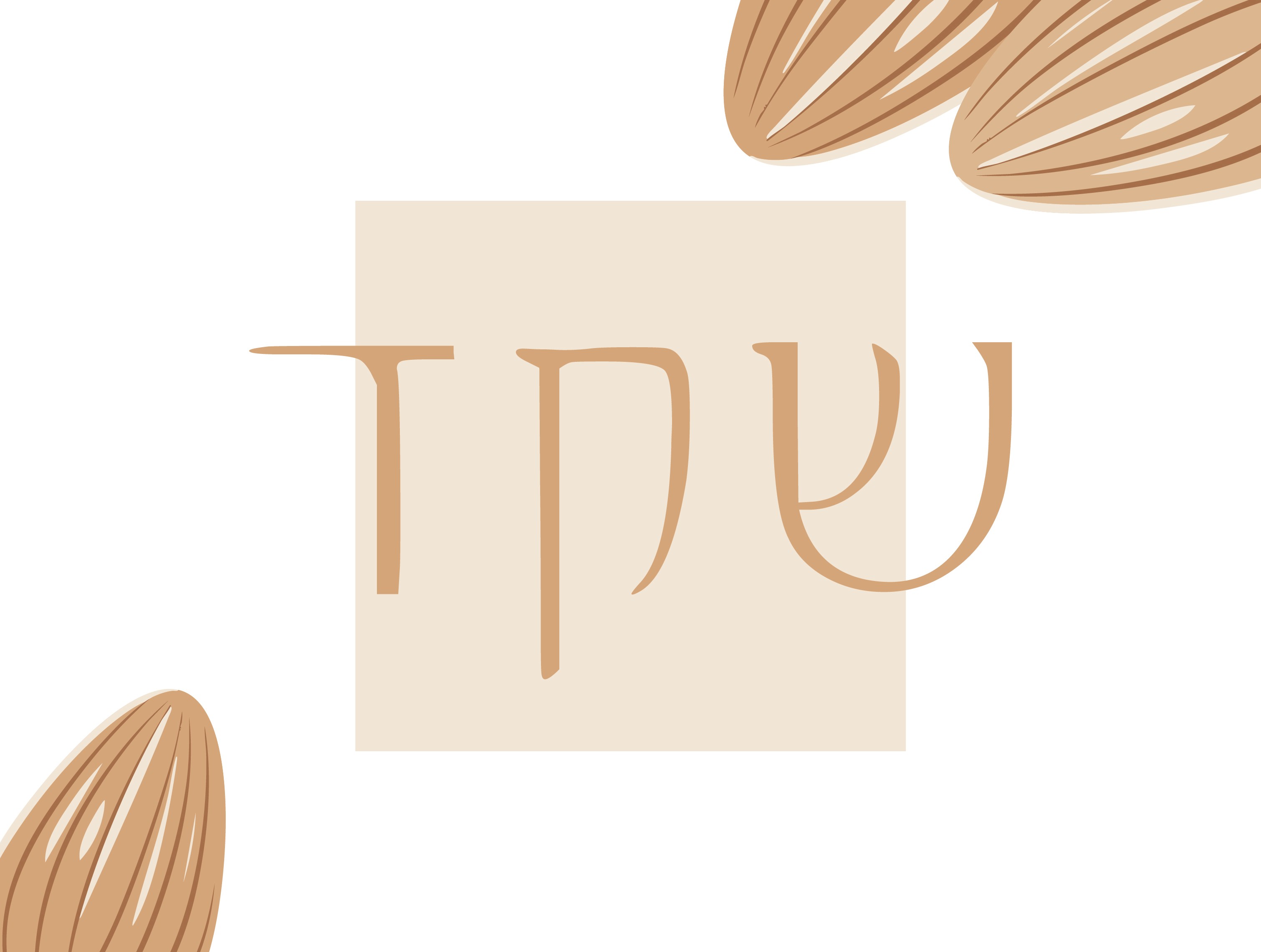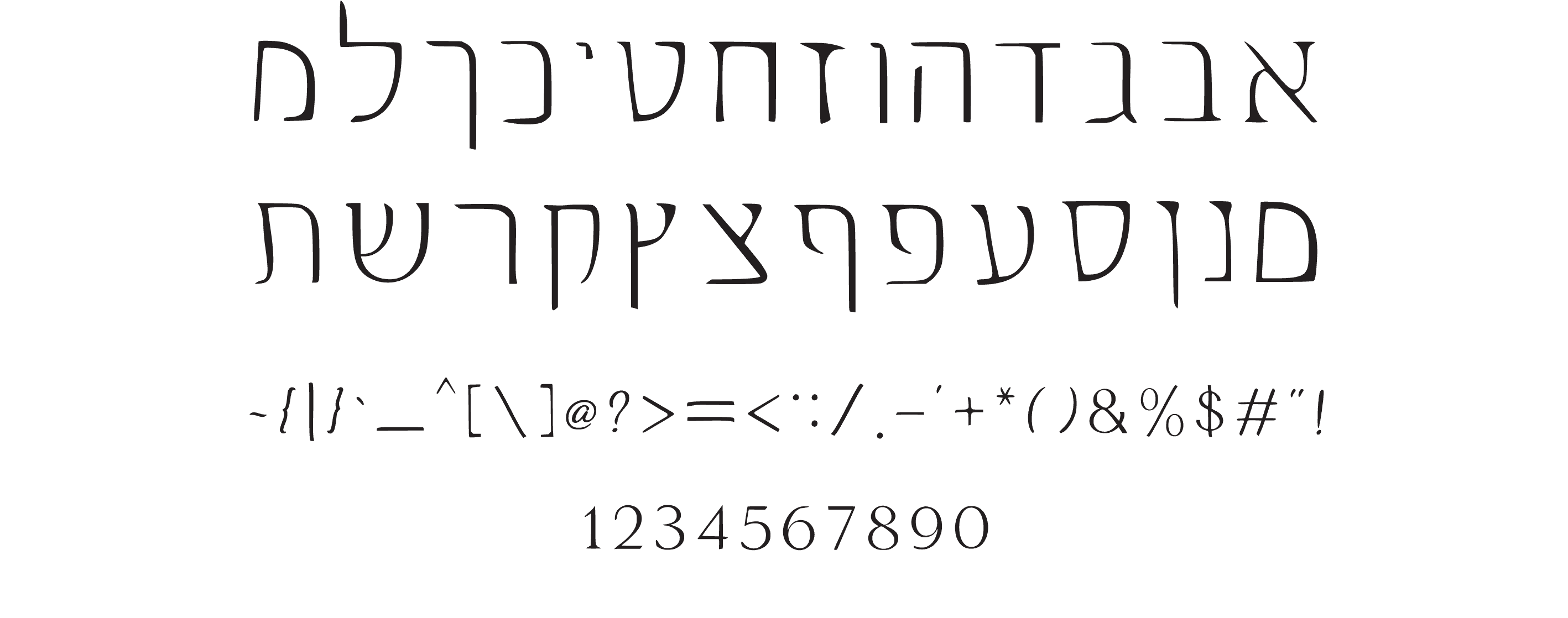
שקד פונט
A free and delicate Hebrew font, suitable for titles, logos, and personal designs with a natural and elegant touch.
שקד — פונט עם טעם של רגעים פשוטים
יש פונטים שבאים לעצב, ויש כאלה שבאים ללטף.
שקד נולד מתוך אהבה לקווים רכים, נקיים, כמעט כמו קליפה של שקד שזה עתה נסדקה.
הוא משלב אווירה טבעית עם נגיעות של אלגנטיות מחויכת — מושלם לכל עיצוב שרוצה להיות אישי, חמים, אבל עדיין מלא שיק.
איפה הוא מרגיש בבית?
✿ ברכות אישיות
✿ עיצובי טבע וקיימות
✿ לוגואים עם אופי רך
✿ בלוגים ומיתוג אישי
למי הוא מתאים?
למעצבים, בלוגרים, בעלי עסקים קטנים וכל מי שמחפש פונט עברי עם נשמה.